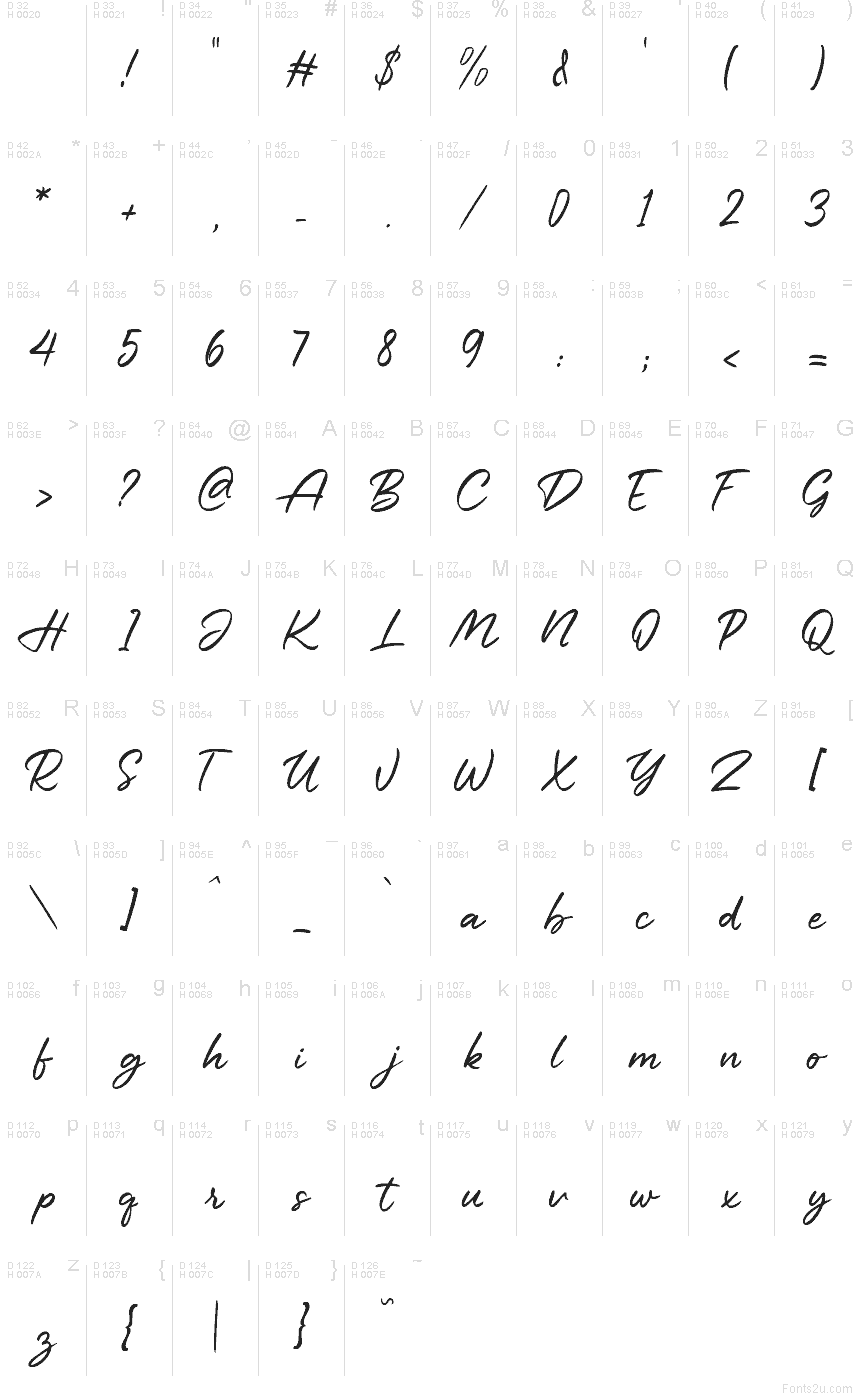
Johnston Airline od BlackFridayFont je bezplatné ručně psané písmo, pro které jsou typické dlouhé, plynulé tahy a přirozený kurzivní rytmus. Písmena působí lehce a vzdušně, s širokými otevřenými smyčkami a jemnými spoji, díky čemuž styl zůstává uvolněný a nikoliv formální.
Tento pohyb dodává krátkým názvům a titulkům přirozený šmrnc při použití v brandingu, na přáníčkách, obalech, jídelních lístcích či grafice pro sociální sítě. Johnston Airline se skvěle hodí i pro podpisy a citáty, kde jeho rozmáchlé začátky a konce vytvářejí osobitý vzhled, aniž by působil ztuhle nebo příliš zdobně.